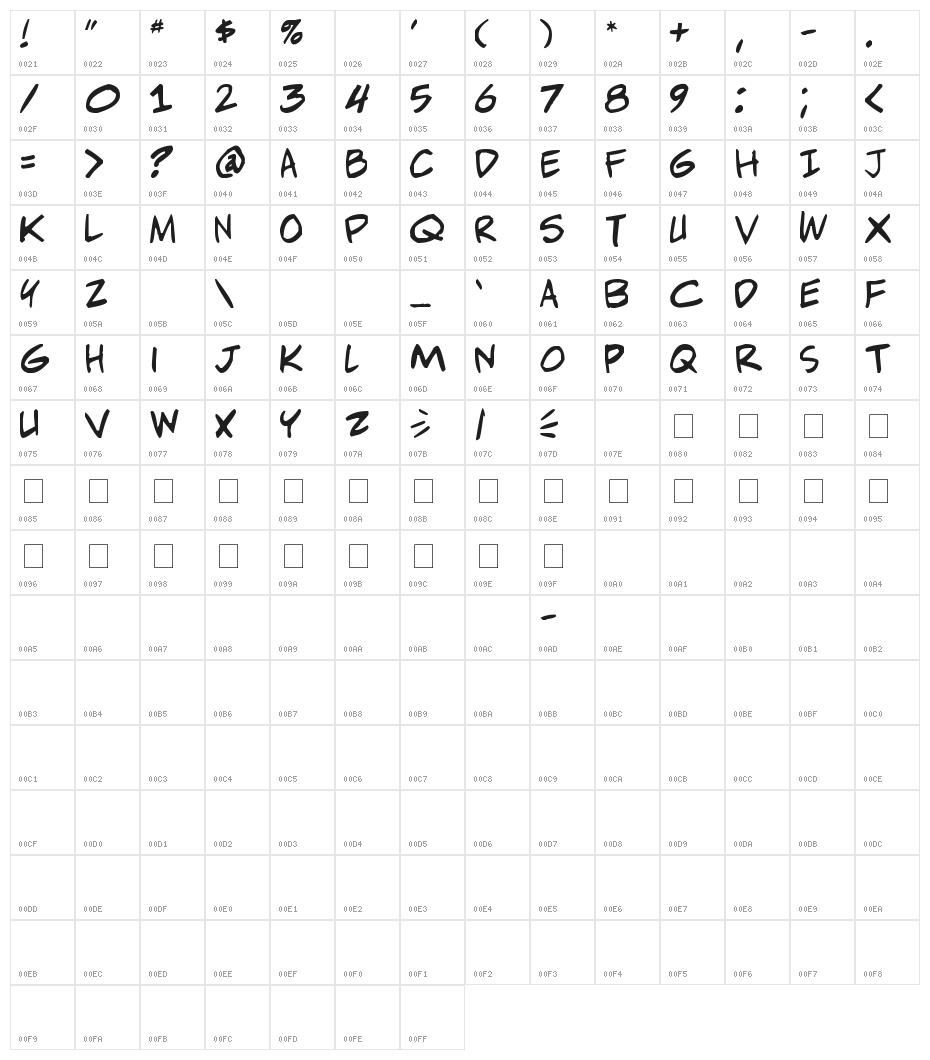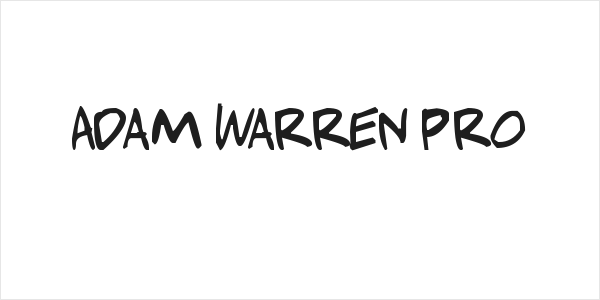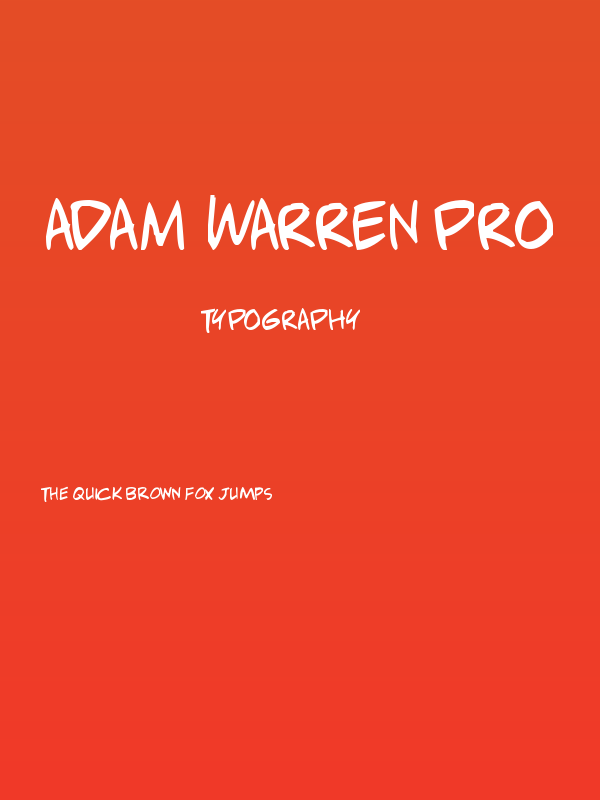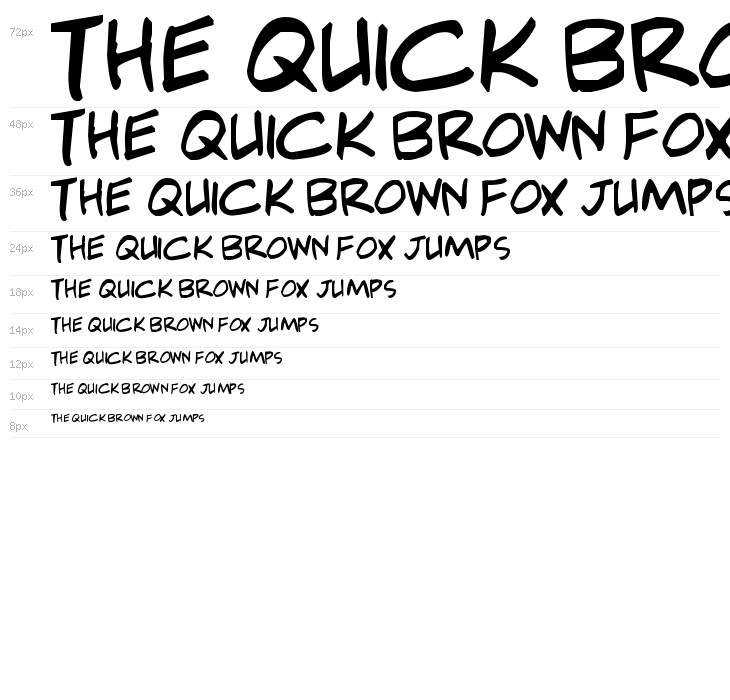
Adam Warren pro Font
| Stil general | Casual, Playful |
| Caz de utilizare | Headlines, Logos, Informal Text |
| Proiecte propuse | Ideal for greeting cards, posters, social media graphics, and branding projects that require a personal and lively touch. |